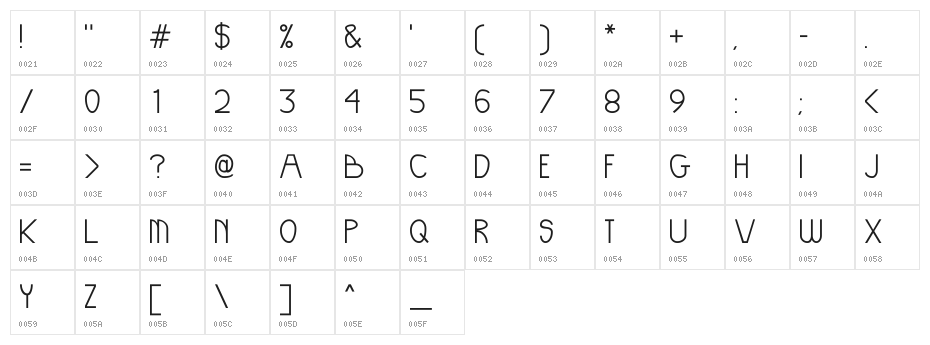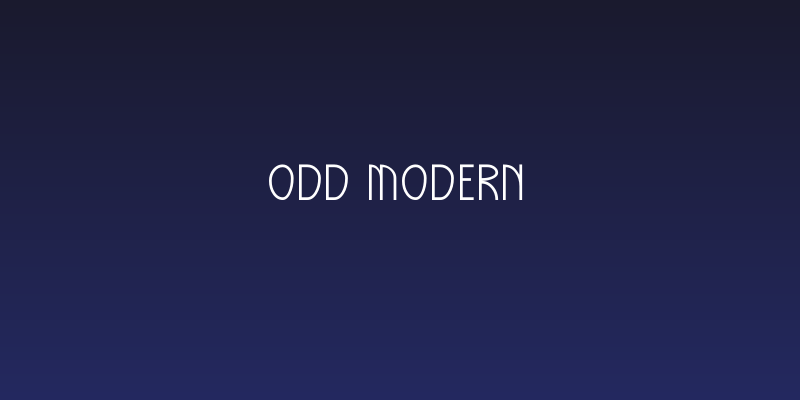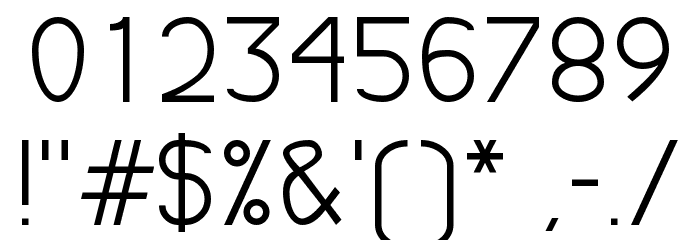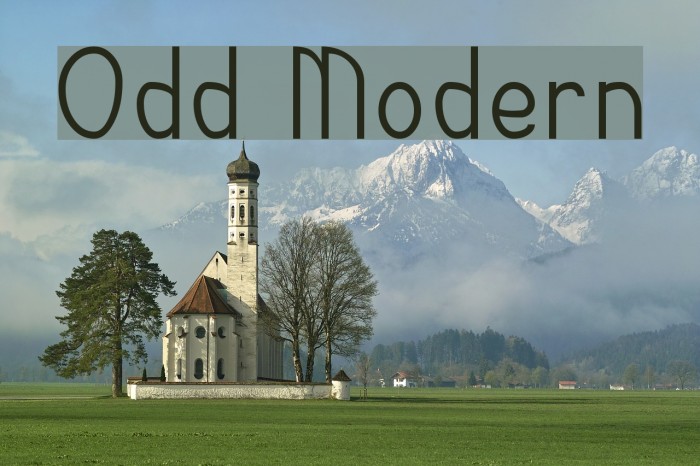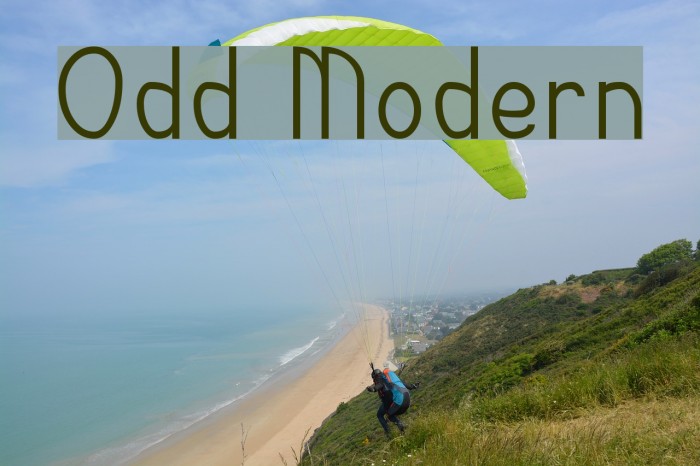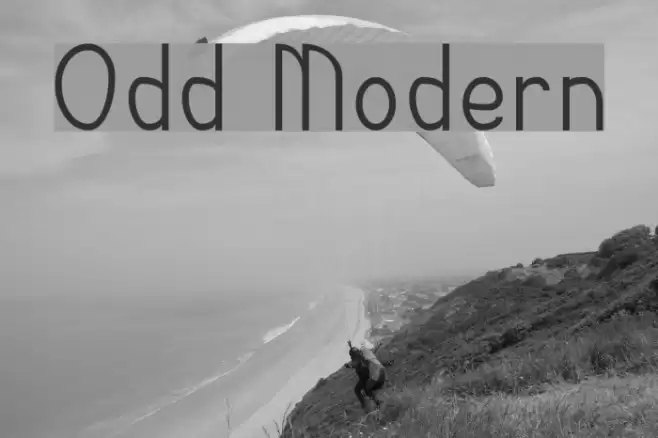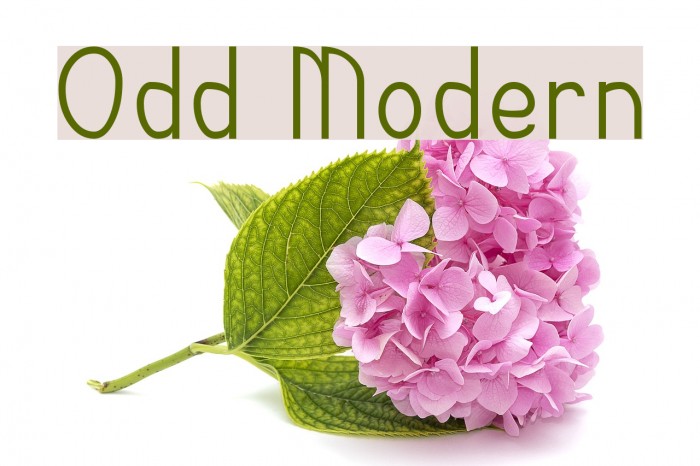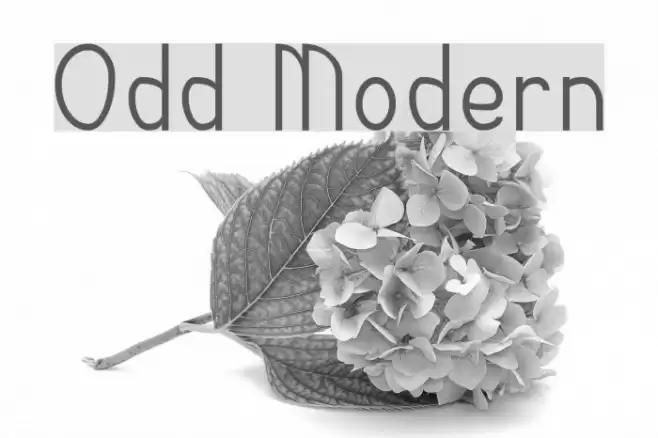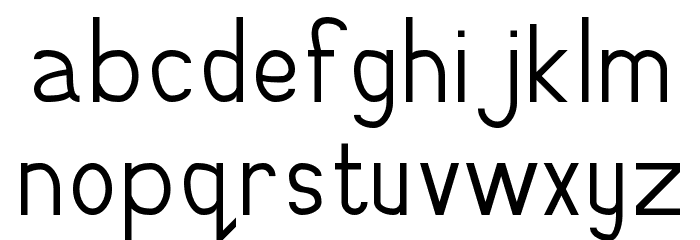
Odd Modern Font
このフォントには 220 文字が含まれています。文字をクリックして詳細を表示。
ODD-MODERN 大文字
ODD-MODERN 小文字
ODD-MODERN その他の文字
| おすすめプロジェクト | Ideal for branding, editorial design, web design, and advertising where a modern and clean look is required. |